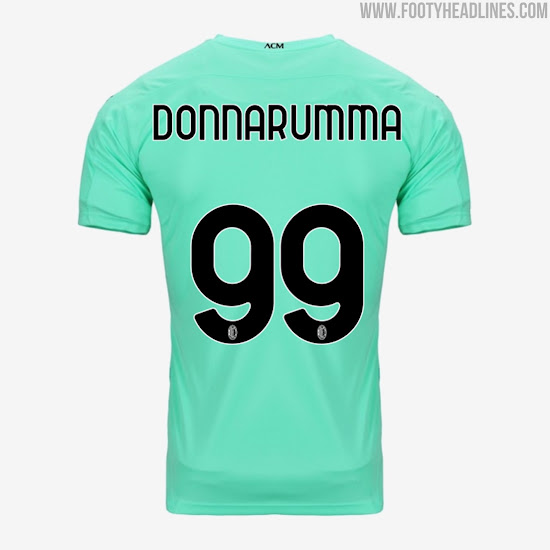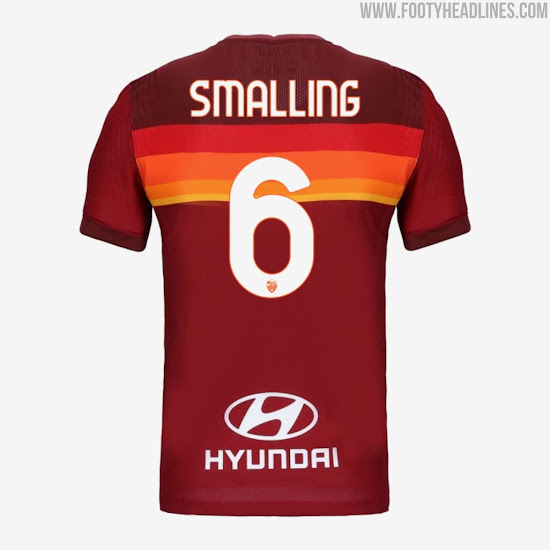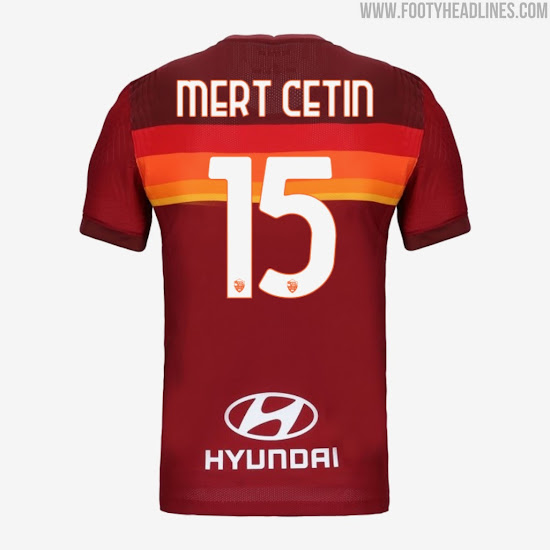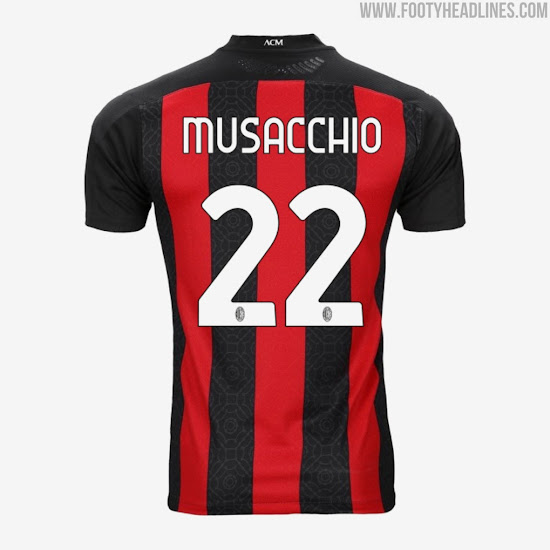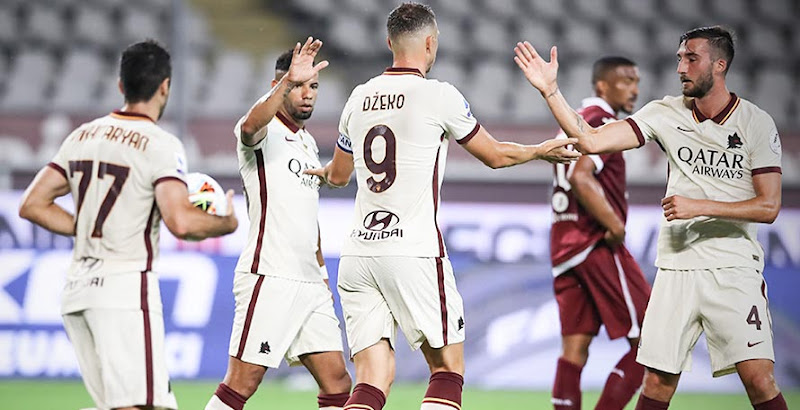
Brandneue ligaweite Serie A Trikot-Schriftart veröffentlicht - Maßgeschneiderte Version für Juventus?
Update: Mit der Veröffentlichung von mehr Serie A 2020-2021 Trikots (darunter Juventus und AC Milan) erhalten wir einen offiziellen Blick auf weitere Beispiele der stromlinienförmigen Serie A 2020-21 Schrift. Anders als die Schriftarten anderer Teams, weisen die Juventus 2020-21 Nummern keinen Rand und ein subtiles Grafikmuster auf - es gibt nach wie vor keine offiziellen Neuigkeiten zur neuen Serie A 2020-21 Trikot-Schriftart.
Die brandneue stromlinienförmige Serie A Trikot-Schriftart wurde zusammen mit dem Nike Inter Mailand 2020-21 Trikot vorgestellt. Es ist die allererste einheitliche Serie A Trikot-Schriftart.
Im Februar 2020 wurde angekündigt, dass die Serie A "unfreundliche" Sponsoren verbieten und eine globale Trikot-Schriftart einführen wird. Es ist noch nicht sicher, ob es sich bei der neuen Nike Inter 2020-21 Schriftart um die neue ligaweite Trikot-Schriftart handelt.
Serie A 2020-2021 Schriftart für Trikots
Die neue Serie A 20-21 Trikot-Schriftart besticht durch ihr modernes und einzigartiges Aussehen. Viele der Zahlen und Buchstaben haben eine einzigartige Form, so dass die Schrift leicht zu erkennen ist.
Am unteren Rand der Zahlen kann jeder Verein sein eigenes Logo einfügen, so wie es auch Vereine aus La Liga tun können. In anderen Ligen wie der Premier League haben alle Mannschaften das Logo der Liga.
Es gibt bisher kein offizielles Statement über die Schrift
Inter und die Roma haben bereits die neue Trikot-Schriftart mit ihren neuen Nike 2020-21 Heimtrikots veröffentlicht. Die genauen Farben von Nummern, Buchstaben & Wappen von Teams wie Juventus und Milan sind bisher nicht bekannt.